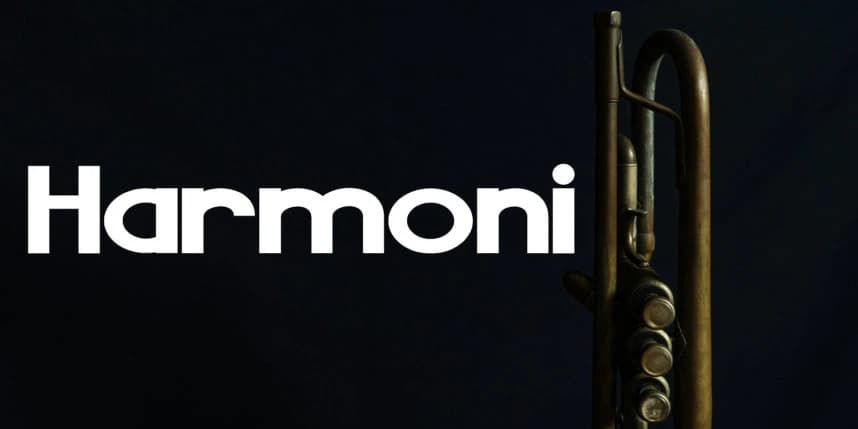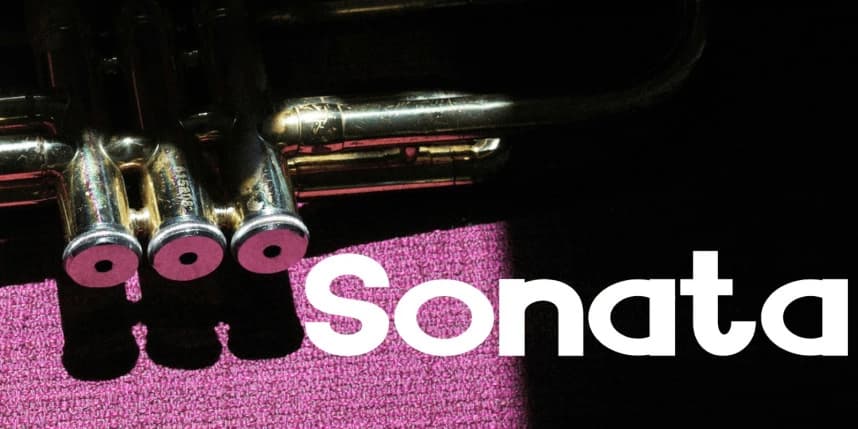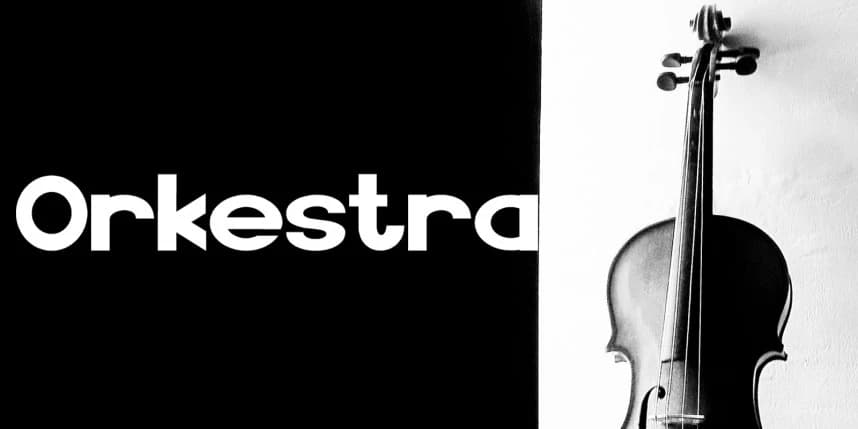
Simfoni Yazı Tipi
Simfoni Font, müzik ve uyum güzelliğinden ilham alan zarif bir yazı tipidir. Yumuşak eğriler ve ince ayrıntılarla tasarımlarınıza sofistike ve romantik bir hava katar. Düğün davetiyeleri ve marka oluşturma için mükemmeldir.
Simfoni Font, müziğin ve uyumun güzelliğinden esinlenen zarif bir yazı tipidir. Pürüzsüz eğriler ve zarif ayrıntılarla tasarımlarınıza sofistike ve romantik bir hava katar. Düğün davetiyeleri ve markalaşma için mükemmeldir.